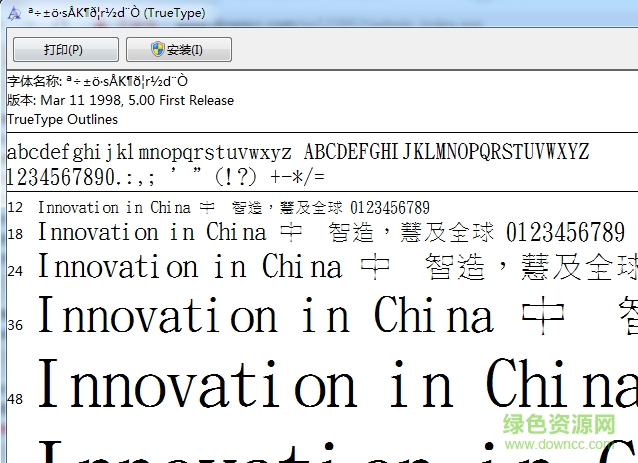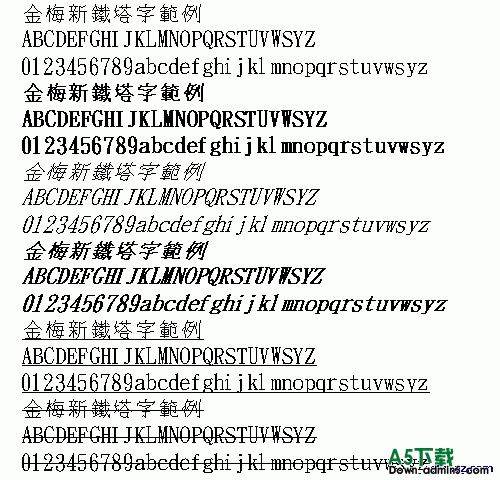
金梅新鐵塔字范例繁字體下載是一款中文簡(jiǎn)體繁體字體,字體使用的范圍十分的廣,而且現(xiàn)在印刷和廣告行業(yè)應(yīng)用十分的廣泛,打印排版看起來(lái)也很舒服,是非常不錯(cuò)的新字體文件,感興趣的用戶快來(lái)綠色資源網(wǎng)下載吧!
如果從設(shè)計(jì)的純角度來(lái)講,運(yùn)用的也是非常少的。筆畫(huà)很均勻并且撇撩筆畫(huà)不尖,使人易于閱讀。由于其醒目的特點(diǎn),常用于標(biāo)題,導(dǎo)語(yǔ),標(biāo)志等等。當(dāng)然常見(jiàn)的標(biāo)題、導(dǎo)語(yǔ)采用的是方正字庫(kù)里的粗黑,大黑,中黑,而不是我們WINDOWS里自帶的。